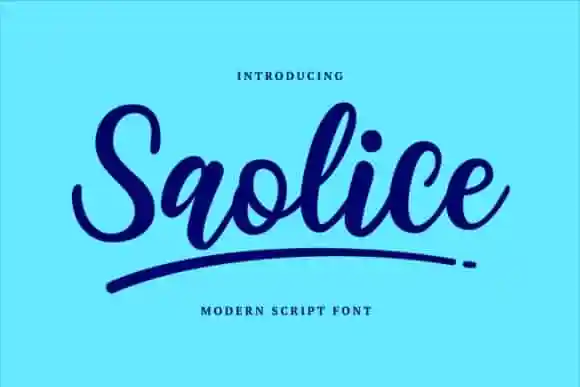
Descobrimos Saolice Script Font na 99designs, uma fonte script que traz a essência do desenho à mão livre para seu projeto digital e impresso. Inspirado em assinaturas personalizadas de clientes, o designer brithostype criou este recurso exclusivo para criar um forte impressiono de marca pessoal nos seus projetos digitais. Saolice é uma fonte simples e encantadora que traz a sensação do traçado humano. Foi desenvolvida com os olhos voltados para múltiplos tipos de projetos, desde cartões de agradecimento e convites até livros infantis e citações. Adicione Saolice a cada ideia criativa e observe como ela destaca seu trabalho. Este é um recurso ideal para aqueles que procuram personalizar seus materiais digitais com uma fonte que não apenas se destaca, mas também convida o leitor ao mesmo tempo. Saolice é uma escolha inteligente para designers gráficos apaixonados por criar experiências únicas em suas criações.